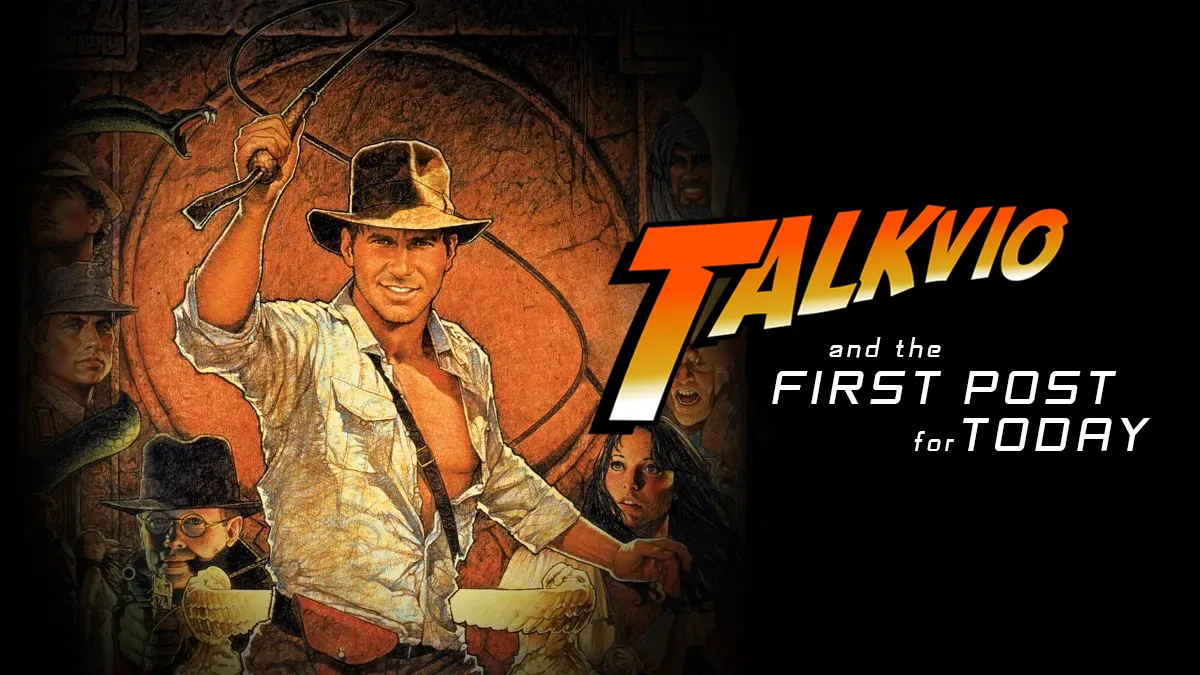
Если вы хотели бы использовать в своих презентациях или видеороликах кино-шрифты, или просто хотел бы с ними ознакомиться – эти посты для вас.
Чаще всего в кино используют довольно простые шрифты, но подают их так, что выглядят они весьма дорого и красиво. Но также могут использоваться и специально созданные для фильма шрифты или различные модификации уже имеющихся.
Чтобы немного приоткрыть эту тему, предлагаю взглянуть на 5 показательных примеров.
Для названия фильма «Индиана Джонс» создатели использовали небольшую модификацию шрифта «SF Fedora», которая слегка округляла некоторые буквы. Им выполнено и название картины и прилегающие к нему описания серии, по типу «в поисках утраченного ковчега».